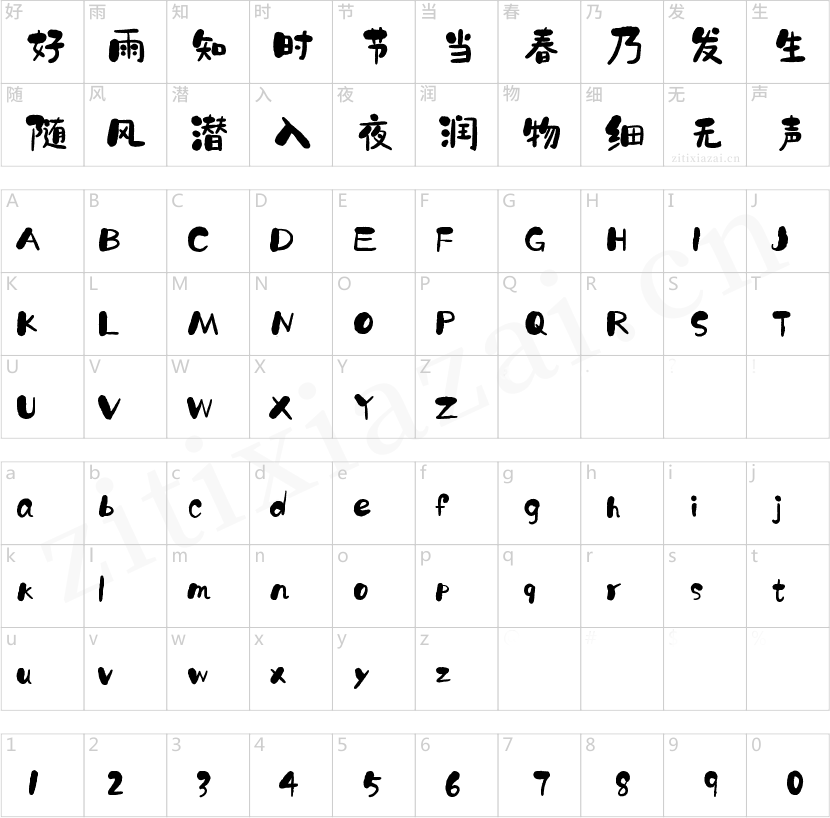
字魂石头体
字魂石头体,这款字体结构工整、笔画清晰,兼顾美观与易读性,适用于标题、正文、海报、包装、LOGO 等多种场景。字形优雅稳定,风格百搭耐看,适配日常排版与创意设计,让文字呈现更舒适、更具质感。字魂石头体一笔一画,皆是细节,以均衡的比例、流畅的线条打造舒适视觉体验,字形端正大气,风格简约现代。无论是商业设计、品牌宣传还是日常排版,都能轻松驾驭,让文字更有格调与力量。字魂石头体字体下载。